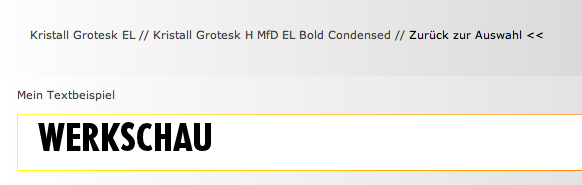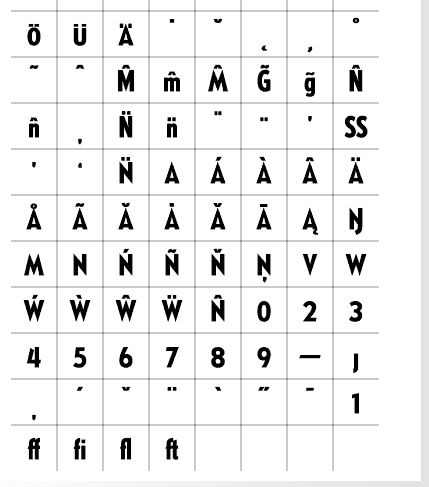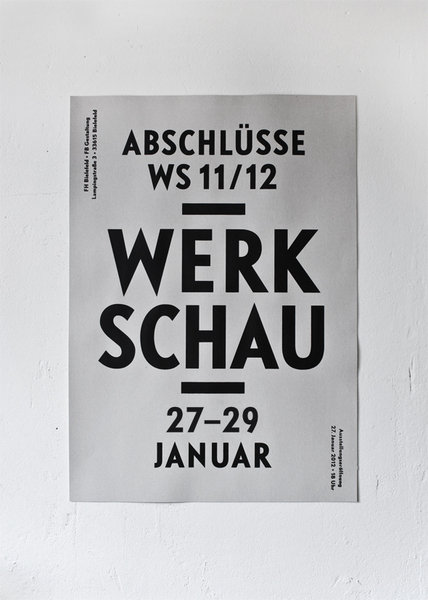
Plakat Werkschau FH Bielefeld - Welche Schrift?
seit ein paar Tagen ist das Plakat auf Slanted und ein paar anderen Seiten, aber nirgends steht etwas über den Gestalter dazu. Identifont und Whatthefont haben es leider nicht getroffen.
Hat hier jemand eine Idee, um welche Schrift es sich handeln könnte?
mein Tipp wäre eine Abschlußarbeit die auf der schmalen Erbar aufbaut. Wobei nach meinem oberflächlichen Wissen die schmale Erbar immer stumpf war, es also keine spitz-stumpfe Erbar gab.
Mein Tip: Kristall-Grotesk.
Die Grundform ist zumindest sehr ähnlich.